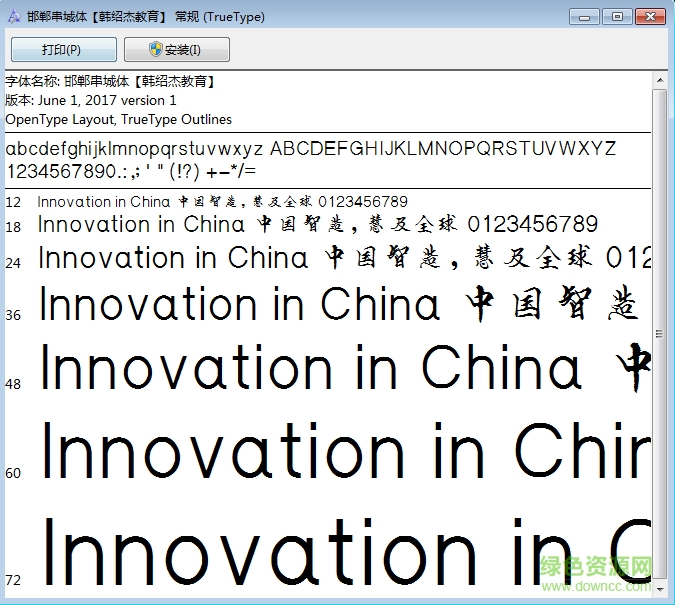
串城體是一款有著邯鄲本土文化象征的書法字體,簡約流暢的字跡給你映入眼簾的好感,喜歡的朋友快來綠色資源網(wǎng)免費下載吧!
電腦字體—“串城體”覆蓋6763個常用漢字,按照GB2312簡體中文編碼表錄入。該字體不僅在找字網(wǎng)上發(fā)布,并且已被錄入《邯鄲字庫》,該字庫擁有邯鄲體、叢臺體、太極體、毛遂體等15種電腦字體,網(wǎng)友們可以免費下載使用,通過網(wǎng)絡(luò)傳播和弘揚趙文化。
串城體”創(chuàng)始人范英聚,現(xiàn)年74歲,河北邯鄲叢臺區(qū)人。8歲時他開始練習書法,以正楷為基礎(chǔ),字體中規(guī)中矩、剛勁有力。1997年,范英聚搬到串城街居住,該街有秦始皇故里、回車巷、慈禧行宮等文化古跡,周圍零零散散留存著磚瓦拓片,范英聚每天光顧,現(xiàn)場拿毛筆臨摹?!斑@些磚瓦拓片上面刻有篆書、隸書等字體,字里行間突顯了將相和中的和文化。我受此啟發(fā),寫字逐漸由剛勁有力轉(zhuǎn)化為剛?cè)岵杳苡兄?,總體原則遵循和文化?!?/p>